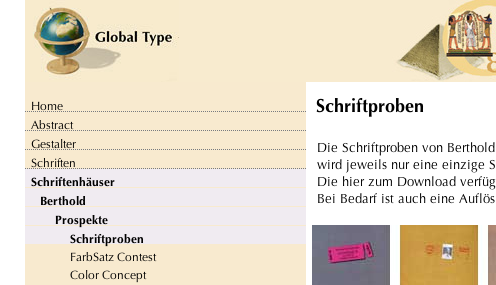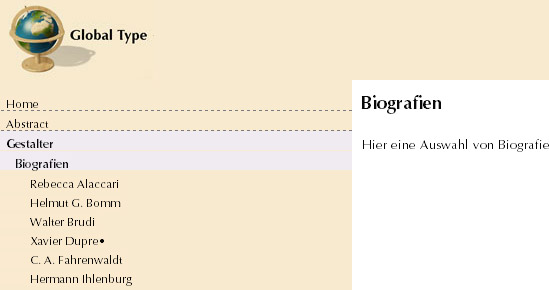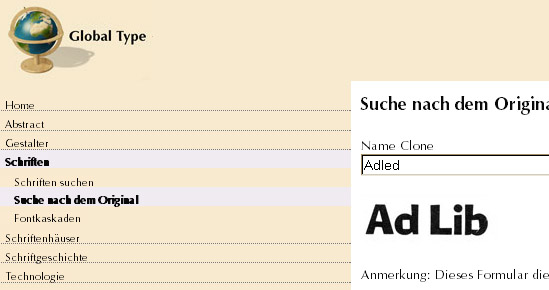
Hm – die Optima fand ich schon ziemlich klasse am Monitor, war vor zwei Jahren ein Überraschungsfund. Bei mir sieht sie so aus:
Mein Screenshot war übrigens Safari 2.0.4 unter Mac OS Tiger. Ich dachte immer, wer mit IE unterwegs ist, ist kein Typograf. :wink:
das erste war firefox
Das hier ist Firefox 2.0.0.3 unter 10.4.9:
Am Firefox liegt es also wirklich nicht. Kann es sein, daß Deine Optima irgendeinen Schuß hat?
naja, ich würde es nicht machen.
Solange sich da nicht noch andere melden, daß es Probleme gibt, würde ich bei der Optima bleiben. Ich halte sie absolut für eine der am angenehmsten am Bildschirm zu lesenden Schriften, wobei ich unter »angenehm« halt noch mehr verstehe als »Buchstaben lassen sich gut unterscheiden«.
Roberts Screenshot kam sicher vom PC und dann greift im schlimmsten Fall eine installierte PostScript-Variante, die für sowas alles andere als geeignet ist. Die Mac-TrueType-Variante ist ja speziell für diesen Einsatz optimiert.
Ich kenn das Problem auch von der Lucida. Sie wird ja von Mac-Webdesignern sehr gern verwendet, aber wenn dann am PC als Ersatz die Lucida-Sans als Type1 angezeigt wird, kann man fast gar nichts mehr lesen.
Ja, die Browser können mit der Postscript-Metrik wenig anfangen --> Es sieht sehr seltsam aus.
Ist fraglich ob es sinnvoll ist eine Schrift zu wählen, die sehr viele User entweder nicht haben, oder in einer Version, die nicht bildschirmkopatibel ist.
Also, ich will ja gar nicht auf der Optima beharren, wenn das wirklich soviele Probleme macht. Andererseits ist sie jetzt schon eine Art Hausschrift für das Projekt, nicht nur auf der Website, sondern auch bei den Präsentationen oder für Drucksachen (auch BB und VKs). Ich dachte, die Eintragung im CSS käme nur bei Leuten ins Spiel, die sie selbst auch haben (natürlich auch korrekt installiert), und dass ansonsten quasi ein „Fallback“ auf die anderen aufgeführten Optionen (sans-serif etc.) stattfindet.
Nach meiner Webstatistik sehen sich die Leute die Website zu 51,7 % mit Safari, also auf dem Mac, wo die Optima Systemschrift ist, und zu 25 % mit dem Firefox an, 16,7 % – das ist ja nicht so wenig, dass man es ignorieren könnte – nehmen den IE. Könnte mir jemand bitte erklären, warum das CSS dann mit IE nicht funktioniert? Ist das zu verbessern?
Ich habe die Optima nicht in meinem Schriftenordner (System). Als Fallback wird mir Verdana angezeigt. Wenn ich die Optima in meinem Win-Schriftenordner hätte UND ich kein Cleartype aktiviert hätte, dann wäre das – nicht fein. Also lieber per Grafik einbinden*, wenn das schon sein muss, oder einfach sein lassen.
* Das geht (auch bis zu einem gewissen Grad skalierbar) mit der Maßeinheit "em", wenn die Site damit gebaut ist.
Danke für die Möglichkeit auf globaltype zurückzugreifen, egal ob mit Optima in der Nav oder nicht :D
Roberts Screenshot kam sicher vom PC und dann greift im schlimmsten Fall eine installierte PostScript-Variante, die für sowas alles andere als geeignet ist. Die Mac-TrueType-Variante ist ja speziell für diesen Einsatz optimiert.
Ich kenn das Problem auch von der Lucida. Sie wird ja von Mac-Webdesignern sehr gern verwendet, aber wenn dann am PC als Ersatz die Lucida-Sans als Type1 angezeigt wird, kann man fast gar nichts mehr lesen.
genauso ist es. ich habe die opima als t1 für den pc. bei der lucida habe ich ebenfalls probleme, genauso wie es ralf beschrieben hat. es liegt also nicht am browser sondern an der art des fonts. css funktioniert schon im IE, das hat damit nix zu tun. stell dir mal vor es gibt einen freefont der optima heisst und der aussieht wie ein grungefont :x
ok, wird kaum vorkommen, aber ich wäre damit vorsichtig.
notfalls machst du die buttons als bilder bzw. in sifr.
die optima ist beim mac systemfont? seit wann das?
sifr für buttons/menustrukturen kann ich momentan noch nicht empfehlen - selbst sifr3 beta hat noch massive performance-lags bei onmouseover-effekten und mehreren sifr-einsätzen pro seite (die in einem menu ja wohl notwendig wären).
ich würde auch auf die "bewährten" screenfonts zurückgreifen - oder, falls das möglich ist, eine browserweiche für safari einbauen und nur dort die optima verwenden (ich spreche von einer browserweiche innerhalb der css-datei und natürlich nicht per javascript, weiss jetzt allerdings nicht obs für safari eine solche gibt oder nicht).